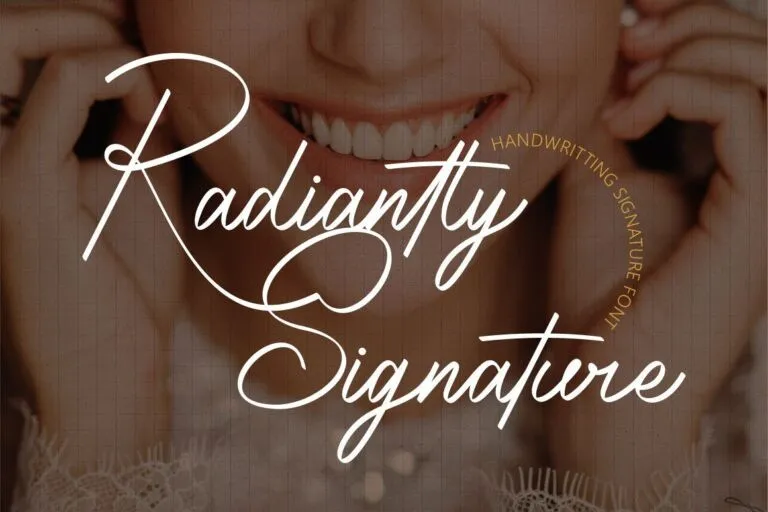
Radiantly Signature Font – Download Grátis
A fonte Radiantly Signature é uma escolha perfeita para quem busca uma combinação arredondada e elegante entre estilo moderno e naturalidade. Ela nasceu do estilo de escrita, combinando formas geométricas estilizadas com um olhar aconchegantemente sofisticado. Esta fonte foi criada pelo designer PutraCetol Studio, na categoria de Script Fonts. A Radiantly Signature oferece uma experiência de letra que é muito semelhante à escrita manual feita com pena, permitindo que você obtenha uma letra quase autêntica quando for utilizá-la em projetos. Seu design está repleto de naturalidade, elegância e luxo, tornando-a perfeita para ambientes que valorizam a harmonia entre modernidade e delicadeza. Perfeito para estilos de escrita legítimos, anotações ou qualquer outro uso criativo onde você deseja adicionar um toque autêntico e sofisticado às suas criações. Seja um projeto de site, uma carta pessoal ou até mesmo sua logo, a Radiantly Signature irá ajudar você a alcançar um look singularmente harmonioso.